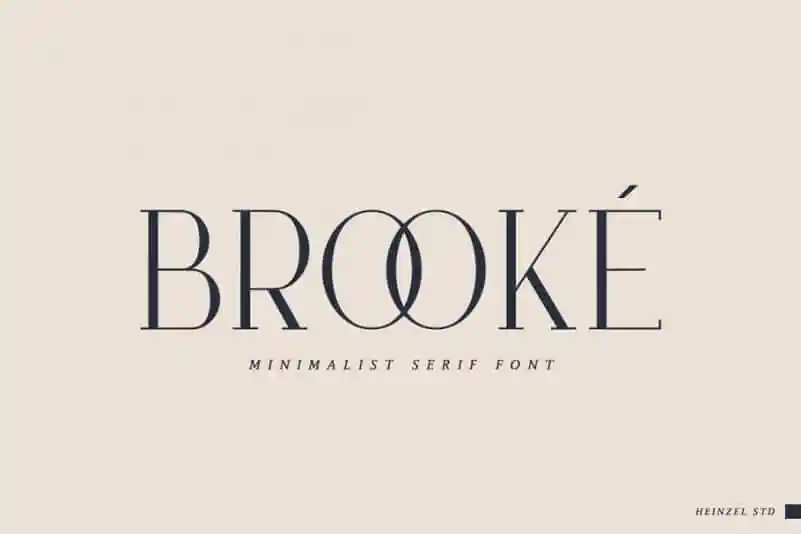
Descubra Brooke Serif Font, uma elegante tipografia serif que oferece ao mesmo tempo modernidade e clássico. Esta fonte foi criada pelo designer Heinzel Studio em 99designs, com uma variedade de opções únicas para garantir facilidade na aplicação. Com seu estilo contemporâneo e minimalista, Brooke Serif é ideal para criar logotipos, trabalhos impressos, collages, texto do corpo e muito mais. Suas linhas simples e arredondadas criam um look minimalista, uma mistura atraente de modernidade com um toque vintage em qualquer projeto. Uma escolha inteligente pode transformar suas criações digitais ou impressas em algo realmente especial.